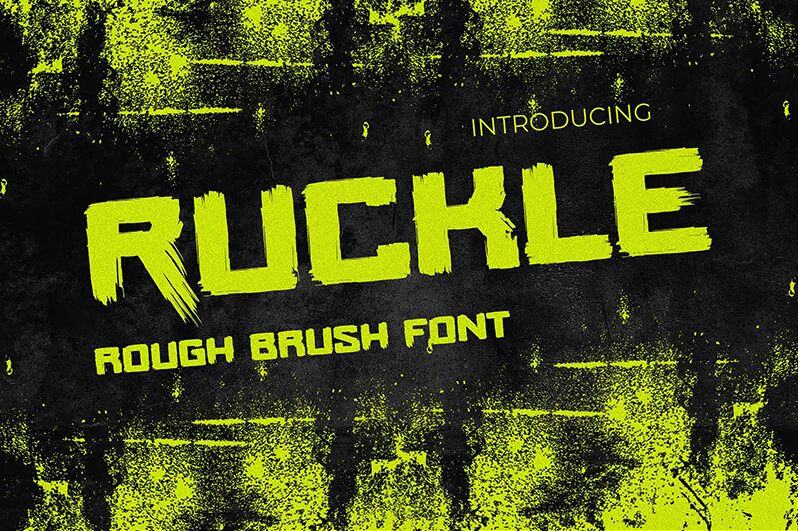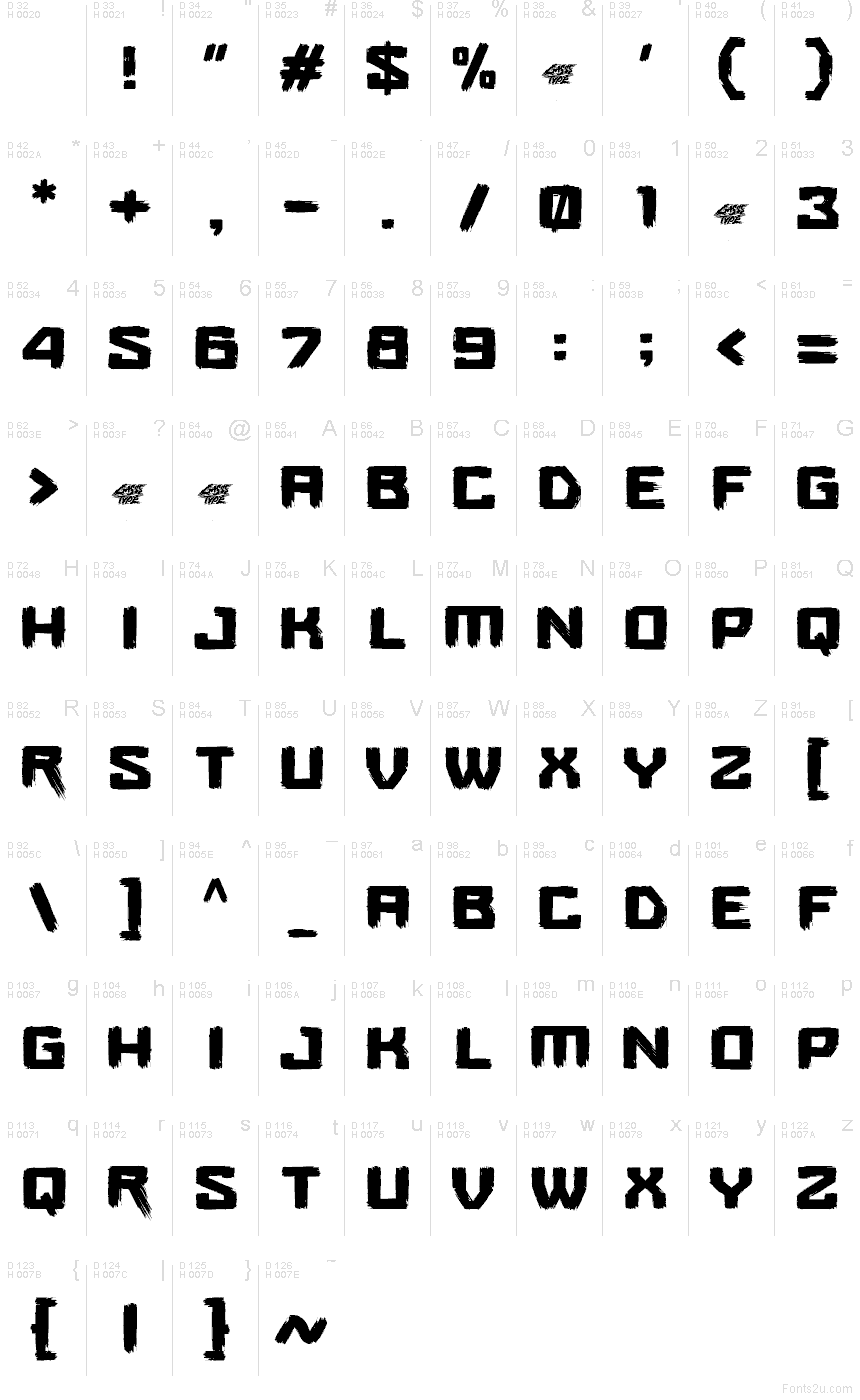
Ruckle, di Gassstype Studio, è un font pennellato gratuito con tratti grezzi, dipinti a mano e bordi strappati che conferiscono a ogni lettera un aspetto usurato. Le forme sono compatte e solide, con irregolarità nel colore e alcuni tratti netti che rendono la scritta grintosa, ben lontana da un look troppo rifinito.
Ruckle è ideale per titoli di locandine, grafiche per band, packaging, abbigliamento e post d'impatto per i social media, dove la texture del pennello fa quasi tutto il lavoro visivo. Questo font gratuito è perfetto anche per banner di eventi e logotipi, perché i suoi bordi irregolari donano un immediato carattere artigianale senza bisogno di decorazioni aggiuntive.